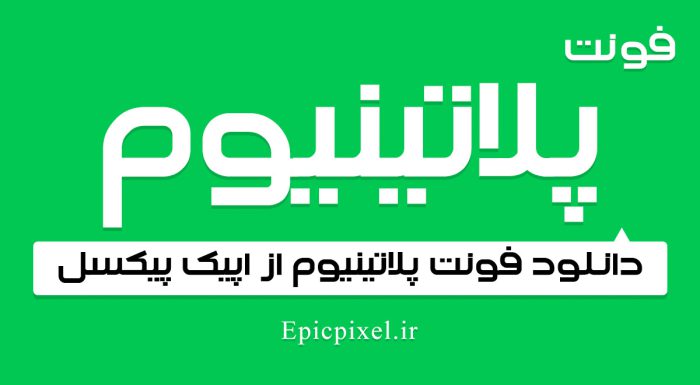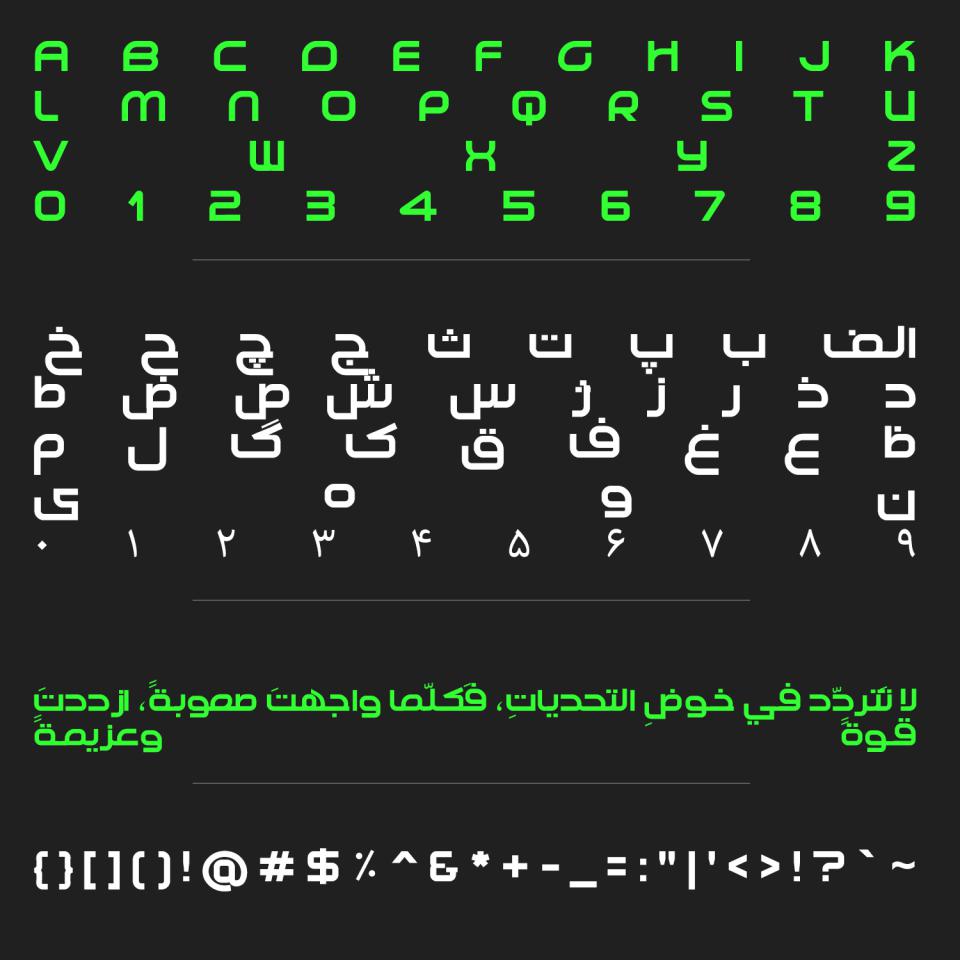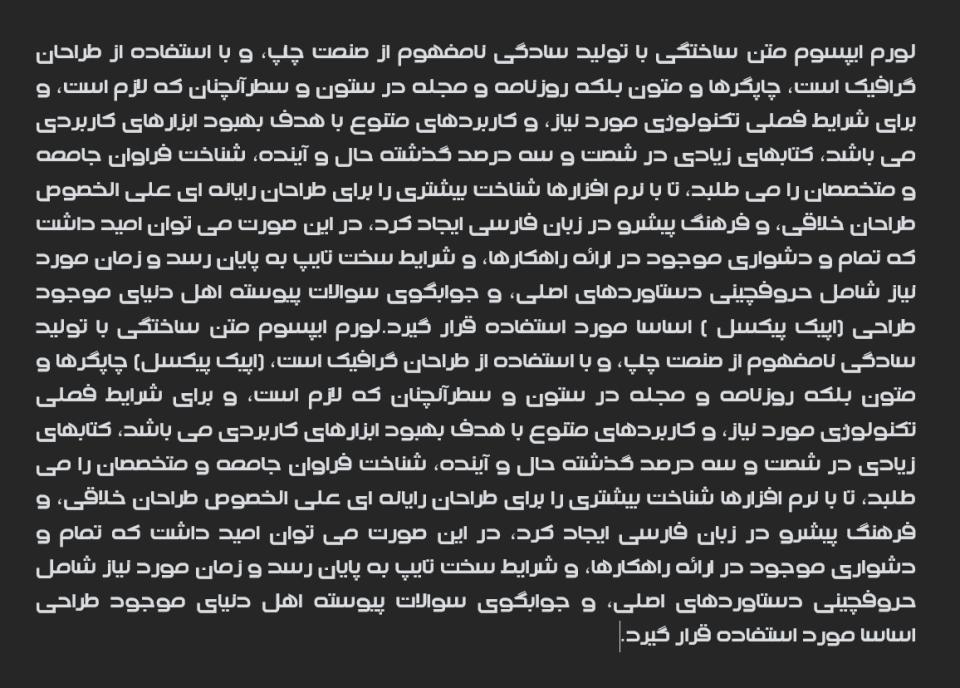
فونت پلاتینیوم فارسی Platinum
فونت پلاتینیوم فارسی، یک انتخاب حرفه ای برای طراحانی است که به دنبال تایپوگرافی های خاص و چشم نواز هستند. این فونت با وزن دو برابر ضخیم تر نسبت به فونت های معمولی، به شما کمک می کند تا لوگوتایپ هایی قدرتمند و متمایز خلق کنید. ضخامت بیشتر این فونت، تاثیر بصری فوق العاده ای به طرح های شما می بخشد و آنها را در نگاه اول جذاب تر می کند.
یکی از ویژگی های برجسته فونت دیما پلاتینیوم، ظاهر دیجیتالی آن است. این ویژگی، به طرح های شما حس مدرنیته و تکنولوژی می بخشد و برای پروژه هایی که به دنبال القای حس نوآوری هستند، بسیار مناسب است. در واقع، این فونت پلی بین سنت و مدرنیته ایجاد می کند و به شما اجازه می دهد تا طرح هایی خلق کنید که همزمان کلاسیک و مدرن به نظر برسند.
این فونت فقط برای طراحی لوگو مناسب نیست، بلکه در تایپوگرافی های خاص نیز کاربرد فراوانی دارد. تصور کنید که می خواهید یک پوستر، جلد کتاب یا یک طرح وب سایت با تایپوگرافی منحصر به فرد طراحی کنید؛ دیما پلاتینیوم با ارائه حسی قوی و متمایز، می تواند به شما در رسیدن به این هدف کمک کند. به عنوان مثال، در طراحی پوسترهای فیلم یا بازی های ویدیویی که نیاز به تایپوگرافی جسورانه و جذاب دارند، این فونت می تواند گزینه ای ایده آل باشد.
با وجود تمام مزایا، باید به این نکته نیز اشاره کرد که ضخامت زیاد این فونت ممکن است در متن های طولانی و با سایز کوچک، خوانایی را کمی کاهش دهد. بنابراین، توصیه می شود که از این فونت بیشتر در عناوین، لوگوها و بخش های کوتاه و برجسته متن استفاده شود. همچنین، از آنجایی که این فونت رایگان نیست، نیاز به صرف هزینه برای تهیه آن وجود دارد که می تواند برای برخی از طراحان محدودیت ایجاد کند. با این حال، با توجه به ویژگی های منحصر به فرد و کاربردهای فراوان آن، دیما پلاتینیوم یک سرمایه گذاری ارزشمند برای طراحانی است که به دنبال کیفیت و تمایز هستند.